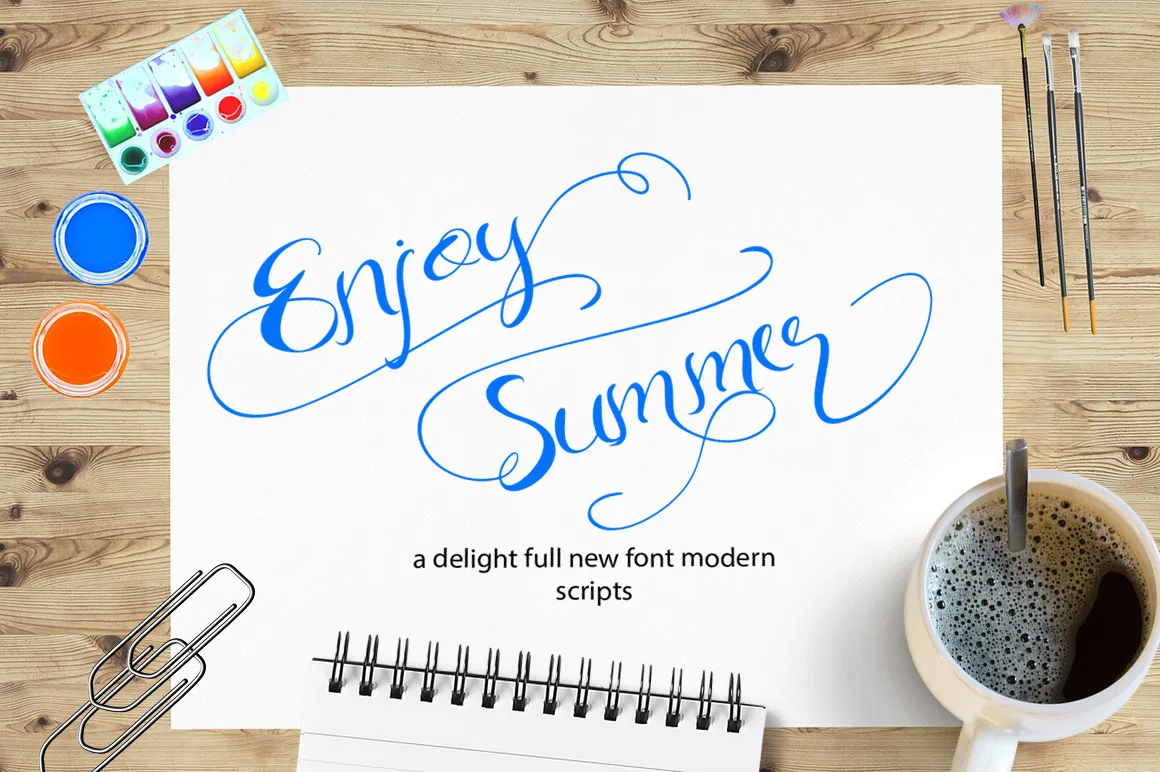
Enjoy Summer Script Font – Download Grátis
A fonte ‘Enjoy Summer Script Font’ é perfeita para aqueles que desejam adicionar uma nota única e vibrante a seus projetos criativos durante os meses quentes do verão brasileiro. Cada letra foi cuidadosamente moldada para garantir um resultado visual impecável, com diversos glifos alternativos que tornam seu texto parecer como se fosse traçado manualmente por uma mão profissional. Seja para aplicar em sua próxima série de citações, criar um cartaz sensacional ou até mesmo desenvolver uma identidade empresarial única, esta fonte é versátil o suficiente para atender a todas essas necessidades. Com seus detalhes refinados e texturas naturalmente vivas, ‘Enjoy Summer Script Font’ vai deixar seu trabalho de arte soar como se fosse um verdadeiro desenho a mão. Seja você designer gráfico, fotógrafo ou editora de blogs, esta fonte oferece a perfeita combinação de beleza e funcionalidade para criar projetos que transpiram verão. E com sua capacidade versátil em várias aplicações, não há dúvida de que essa é uma escolha inteligente para aqueles buscando um toque especial em seus trabalhos.